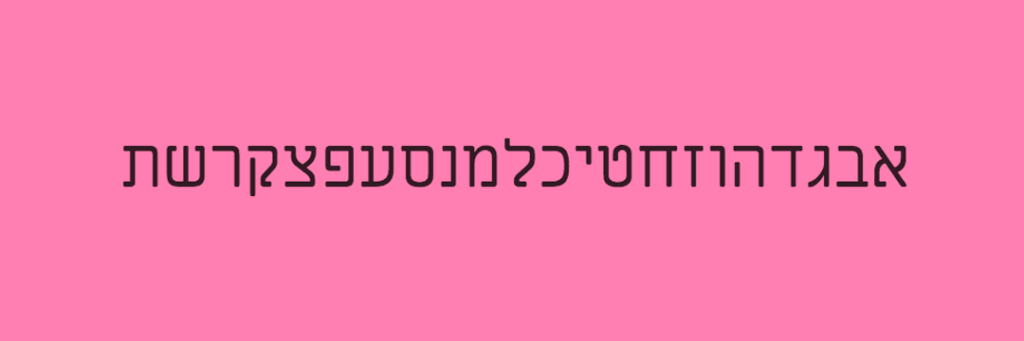
את הפונטים העבריים הקלאסיים שנמצאים היום בשימוש נרחב אפשר למנות ברשימה קצרה ואקסקלוסיבית. ברשימה הזו יש מקום מיוחד לפונט מרים הייחודי שעוצב על ידי מעצב הפונטים היהודי־גרמני רפאל פרנק (ההוא שעיצב את פרנק ריהל) בשנת 1908 בגרמניה. מאז הפך פונט מרים לנפוץ מאוד בקהילות היהודיות דוברות העברית והיידיש ברחבי העולם. לאחר שסיים לעצב את הפונט, החליט רפאל לקרוא לפונט על … המשך לקרוא פונט מרים